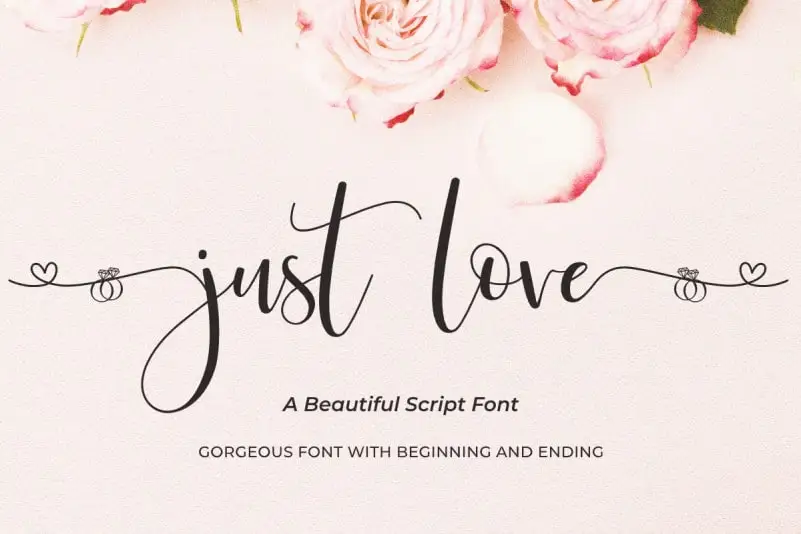
Just Love Script Font – Download Grátis
A Just Love Script Font é uma elegante tipografia escrita a mão que transmite um sentimento relaxado e carinhoso. Ideal para aqueles desejando transmitir uma atmosfera suave e acolhedora em seus projetos, esta fonte vem com uma gama de alternativas perfeitas para criar designes surpreendentemente versáteis. Com uma variedade de linhas curvas fluidas e um conjunto completo de alternativas exclusivas que adicionam profundidade a cada letra, ela é ideal tanto para anúncios profissionais quanto para trabalhos pessoais. Essa fonte PUA, que permite acesso fácil aos gráficos e os swashes, oferece uma variedade incrível de opções que não apenas torna sua vida mais divertida na hora de criar, mas também adicionam um toque único a seu trabalho final. Nada como a Just Love Script para trazer a diversão ao trabalho!